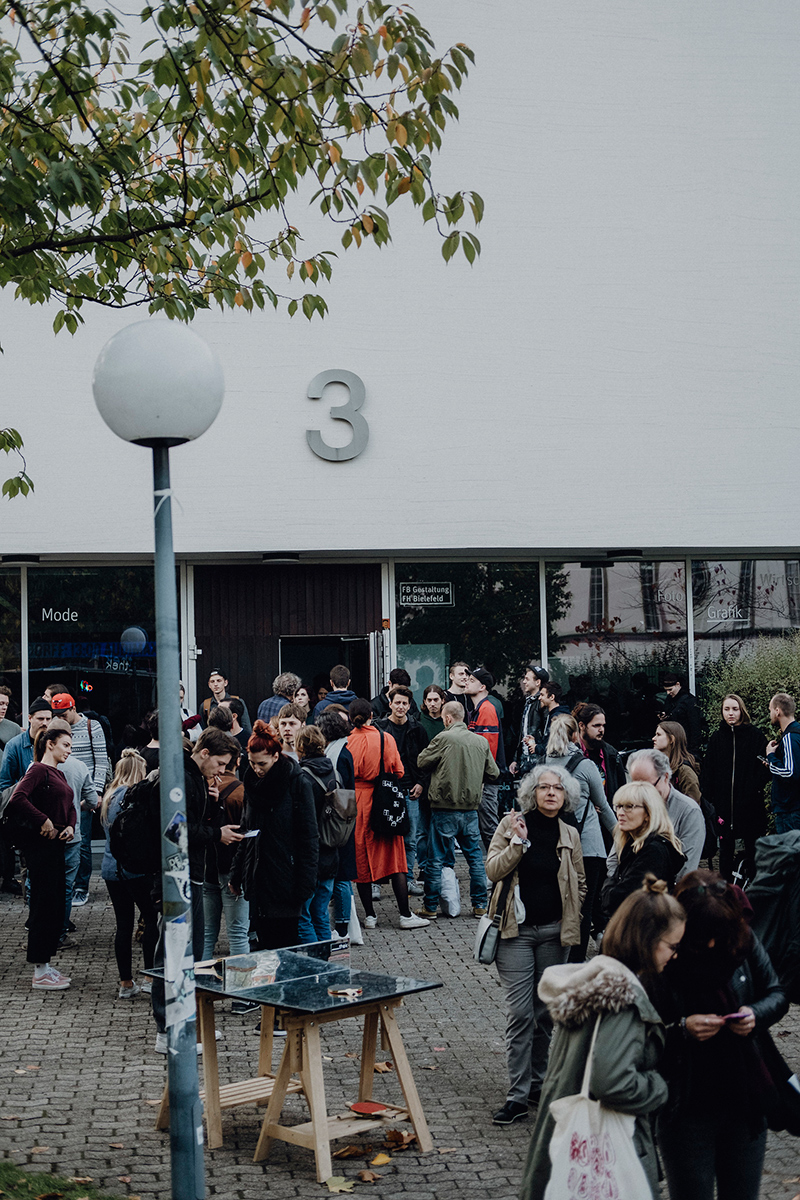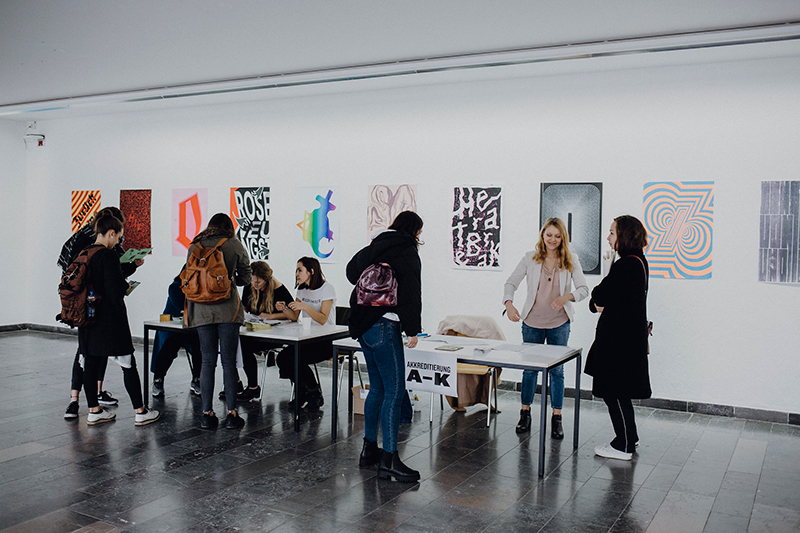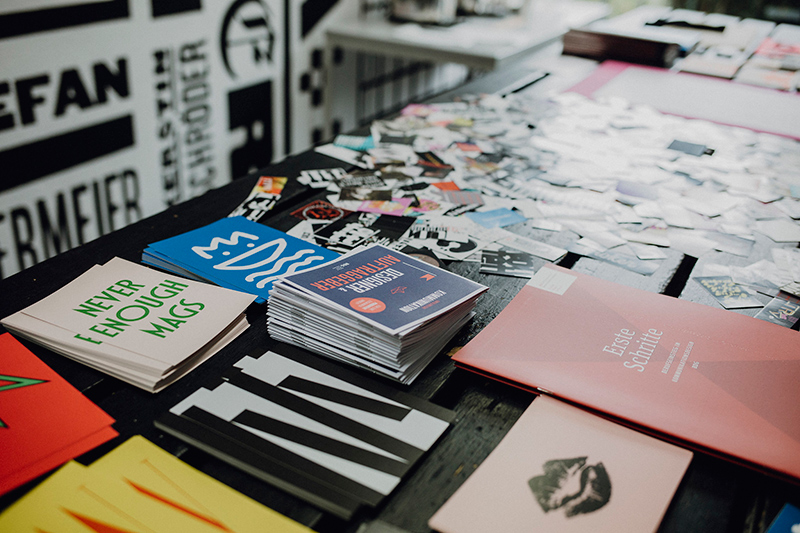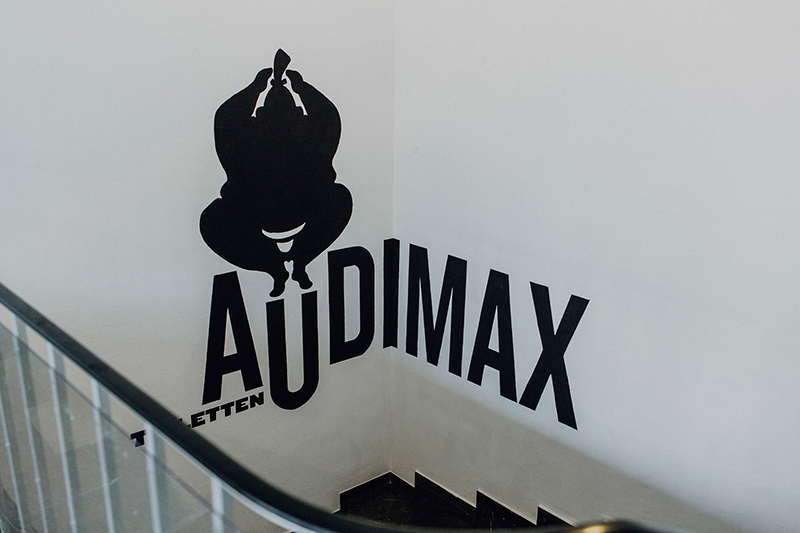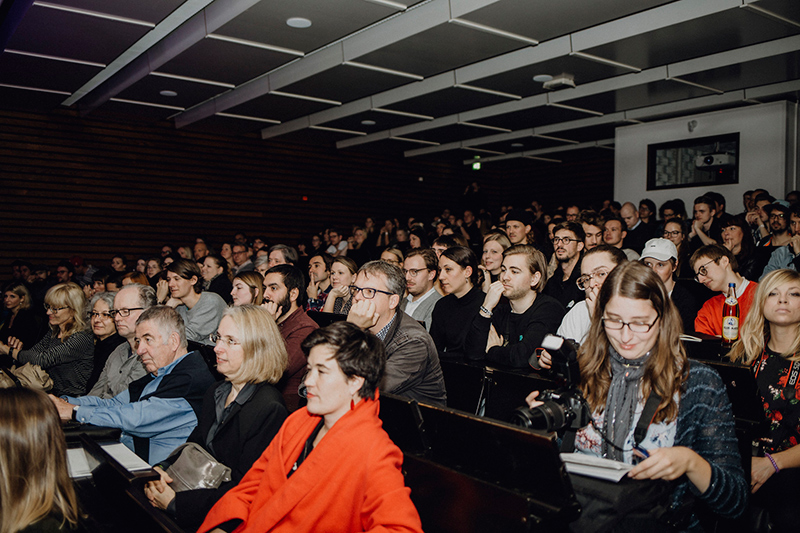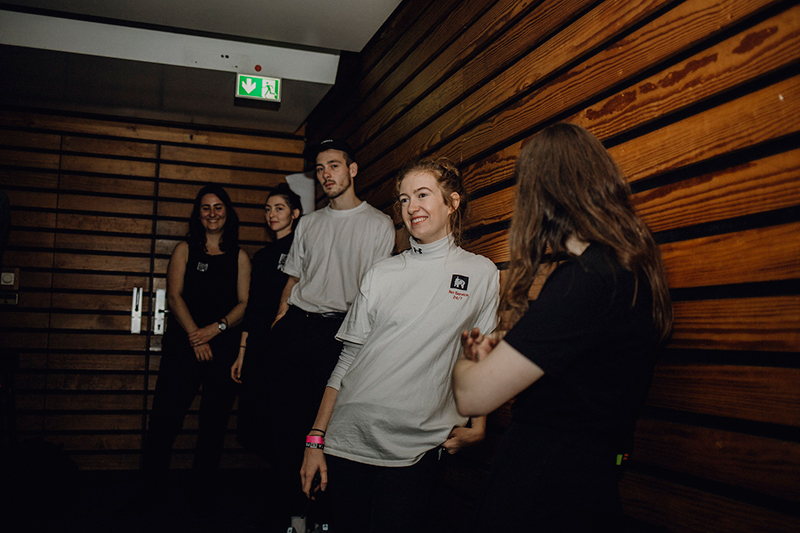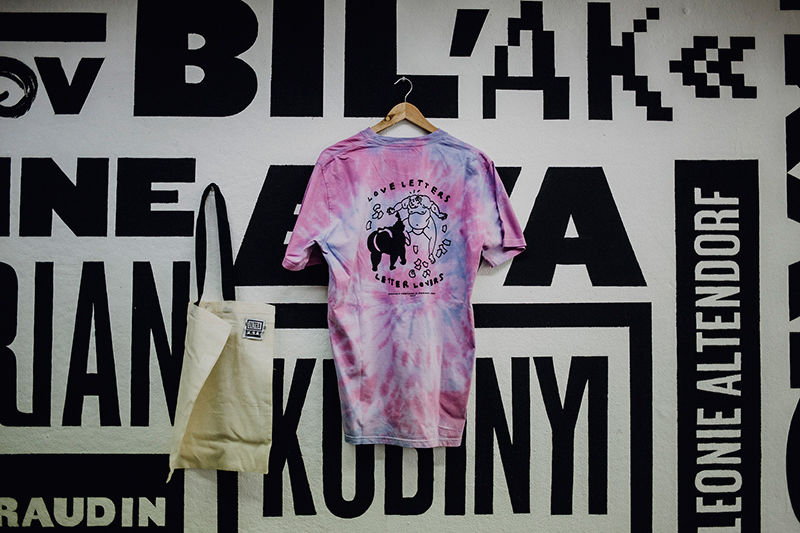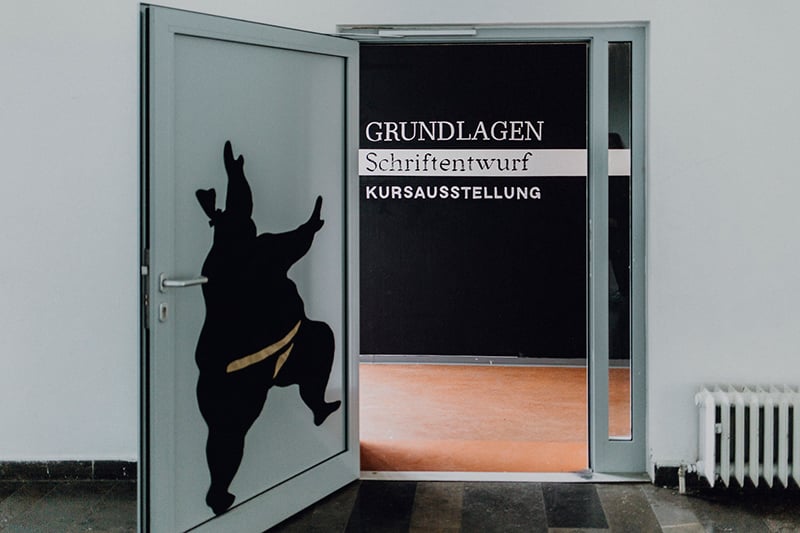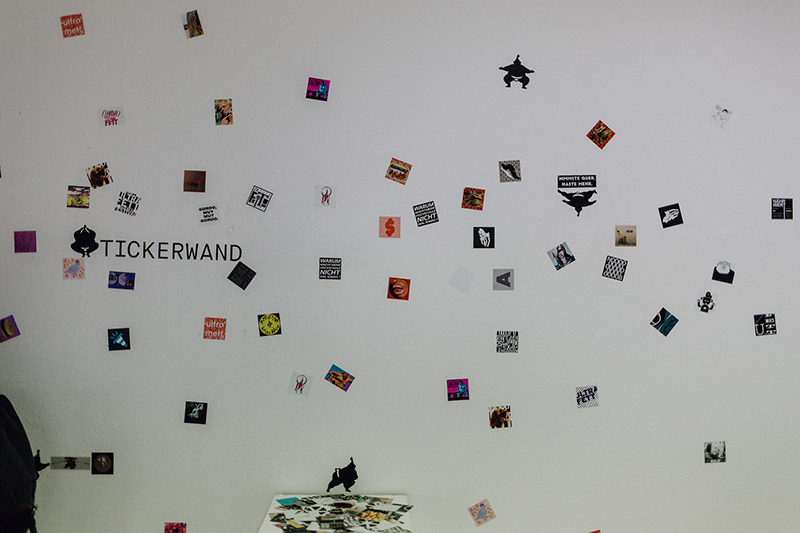
ULTRAFETT, das ist Credo, Ansage, Herausforderung und Aufgabe zugleich und natürlich auch der Name des allerersten Typografie Festivals der FH Bielefeld. Nicht nur mit ihrem Titel hat sich die Veranstaltung sehr viel vorgenommen und es geschafft ein wenig das eigene Format auf den Kopf zu stellen. Es waren zwei »ultrafette«, spannende Tage, auf die wir hier noch einmal zurück blicken wollen.
Dass bei dem neuen Typografie Festival der FH Bielefeld etwas neues versucht wurde, hat man schon am nicht vorhandenen Eintrittspreis bemerkt. Dirk Fütterer und seinem ULTRAFETT-Team war es allerdings wichtig, dass kostenlos nicht wirken sollte wie »nichts drin«. So entstand die Idee, eine kleine Hürde einzubauen. Interessierte sollten also einen Sticker entwerfen, aber dank großzügigem Sponsoring durch Monotype, die FH Bielefeld und den BDG nichts für die Teilnahme bezahlen. Ein toller Trick, der besonders viele Studenten ansprach, die sonst eher wenig Zugang zu größeren Typokonferenzen haben. Die einfallsreichen Stickerentwürfe wurden dann auch wirklich produziert und lagen überall aus.
Typografie stand natürlich ganz klar im Mittelpunkt und wurde in den Vorträgen vielseitig und abwechslungsreich erläutert und interpretiert. Neben der klassischen Verwendung, wie sie etwa Typograf Gerd Fleischmann repräsentierte, waren auch neuere Themen wie Variable Type im Fokus. Die Vorträge wurden zudem in den Pausen durch interessante Paneldiskussionen ergänzt. Toll war auch, dass ULTRAFETT es geschafft hat nicht nur gleich viele Frauen und Männer auf die Bühne zu holen, sondern auch über diese Kategorien hinauseinen guten Mix an Perspektiven bieten konnte. Auch die Ausstellung des Type Directors Club, die man sich am Donnerstag als Abendveranstaltung anschauen konnte, war definitiv ein Highlight.
Insgesamt standen Menschen mit einem besonderen Blick auf die Welt auf der Rednerliste. Kreative, die diese Perspektive nutzen, um ihre persönlichen Schaffensparameter selbst festzusetzen und eine eigene Bildsprache zu finden. Hier fallen unter anderen Gestalter wie Anja Kaiser, Peter Bankov und Josh Schaub auf. Virtuell trifft hier auf reell, 2D und 3D verheddern sich, aus Postern wird Animation und Text verschwimmt mit Bild. Es ist erfrischend zu sehen, wie an allen Seiten die Grenzen des Machbaren erprobt werden, ohne dass das alte, die traditionelle Typografie wenn man so will, seinen Stellenwert verliert . Stattdessen wird es neu benutzt und interpretiert.